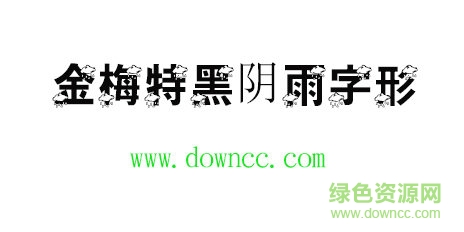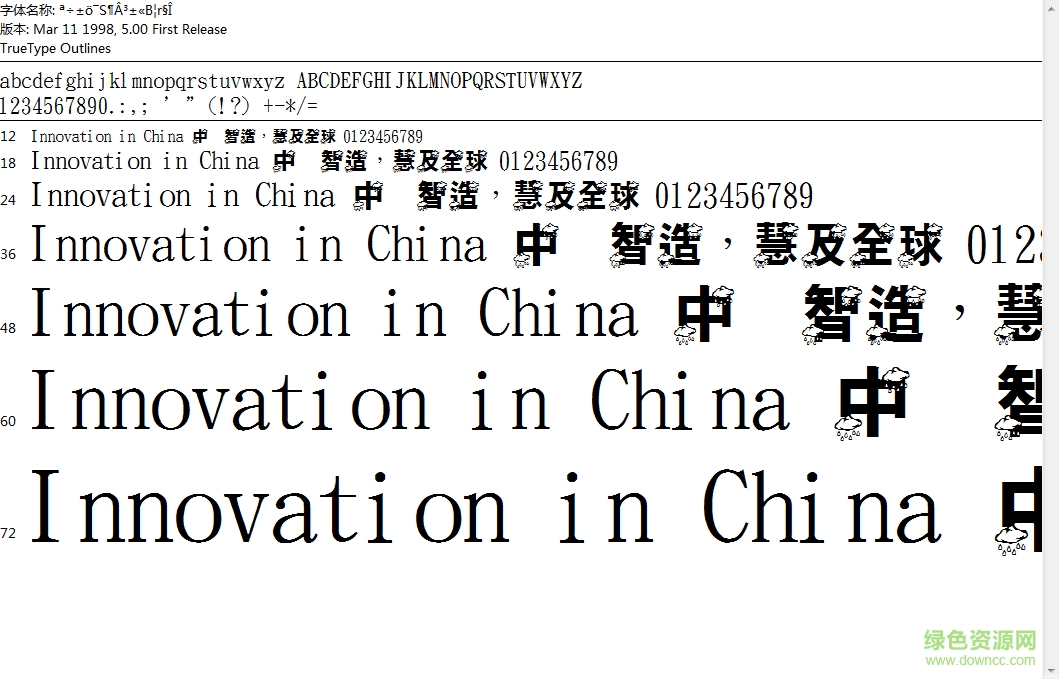
金梅特黑陰雨字形是一款偏卡通風的繁體字體,此款字體每個字上面都有一朵云彩,字形片粗,具有影人注目的效果,應(yīng)用范圍也比較廣泛,適合做特殊廣告平面設(shè)計的朋友使用,而且還是永久免費的哦,喜歡的朋友歡迎來綠色資源網(wǎng)下載!
1.完全支持日文、韓文、繁體中文和簡體中文。
2.筆形方頭方尾、黑白均勻。